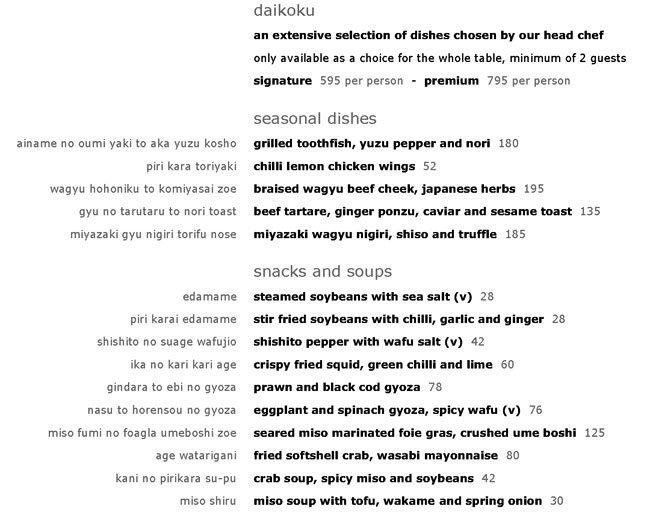
Suche Schrift dieser Menukarte von Zuma
Das Restaurant ist die Japanische Kette Zuma. Die Schrift mit der Anordnung finde ich sehr gelungen.
Ich denke, das ist eine ganz ordinäre Verdana – zumindest wird die auch in den anderen PDFs des Restaurants verwendet.
Herr Martin Schulz, es schient, dass Sie sehr viel Erfahrung mit Schriften haben. Darf ich fragen, welche Schrift Sie für eine Speisekarte für ein Japanisches Restaurant empfeheln würden? Klare, einfache und nicht verpielte Schrift wäre super! Danke.
Wie wäre es mit der JAF Bernini Sans (2012) von Tim Ahrens und Shoko Mugikura? Neutral (»Bernino«) und etwas verspielter (»Bernina«) lassen sich nach Bedarf variieren. In puncto Ausstattung lässt die Schrift kaum Wünsche offen; ein »Arbeitspferd«.
Diese Einschränkungen sind doch schon mal eine gute Grundlage, um bei Schriftanbietern auf die Suche zu gehen: mit den Tags #modern #grotesk #clean – vielleicht noch #contemporary finden Sie bspw. bei Myfonts sicherlich eine etwas exotischere Schrift als die Verdana.
Für eine konkrete Schrift-Empfehlung fehlt mir allerdings jeder Anhaltspunkt, da ich ja nichts über das Restaurant weiß.